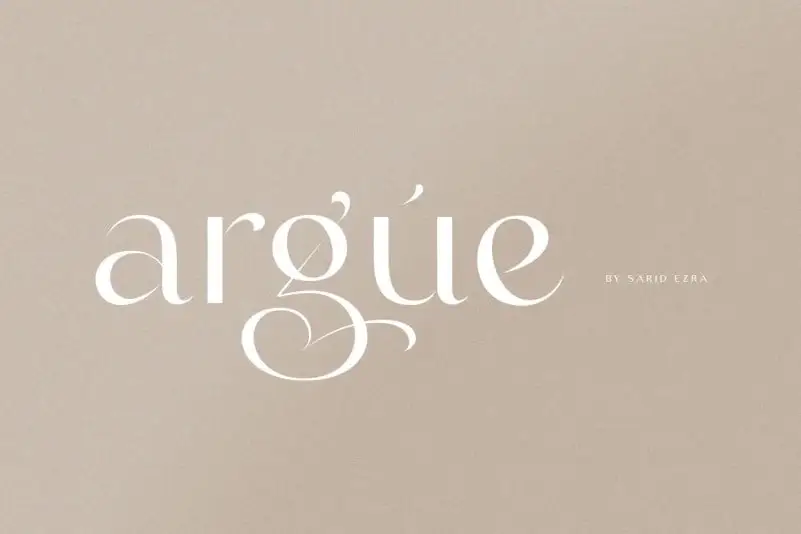
Argue Sans Serif Font – Download Grátis
A Argue Sans Serif é uma fonte moderna e elegante criada pelo 99designs, apresentando linhas simples e sutis baseadas num minimalismo atemporal. Sujeitável a diversas aplicações como cartões de convite para casamento ou até mesmo sua própria marca! Esta fonte oferece suporte a várias línguas, já sendo pré-carregada com encodings PUA que torna o seu uso ainda mais conveniente e sofisticado. O design vem equipado com detalhes elaborados que a fazem um pouco mais estilosa e única no meio de uma variedade de fontes sem serif disponíveis. Este é mais do que apenas uma fonte; ele é uma experiência de estilo para qualquer projeto gráfico que você desejasse criar, desde o mínimo até ao máximo de originalidade e sofisticação.